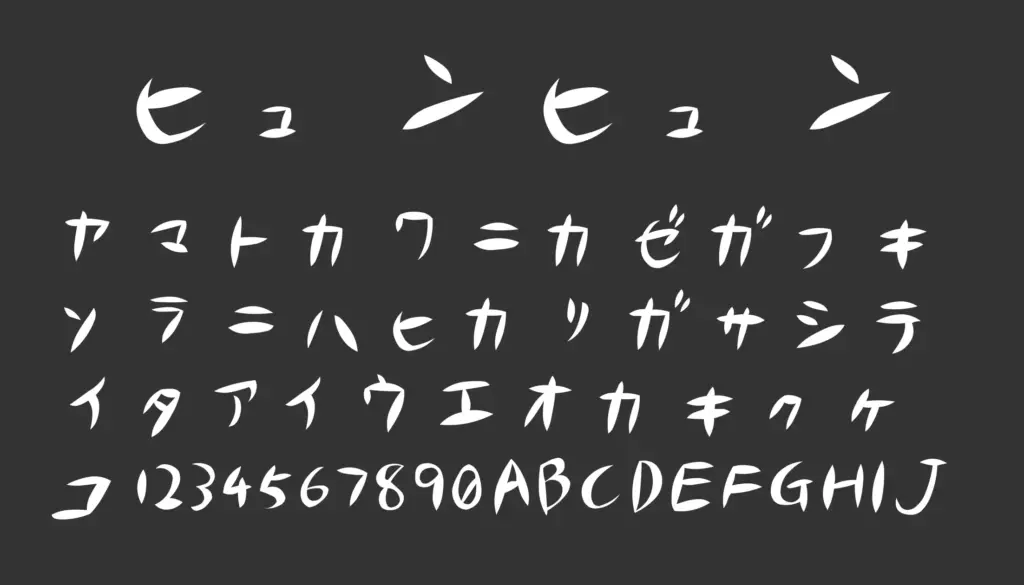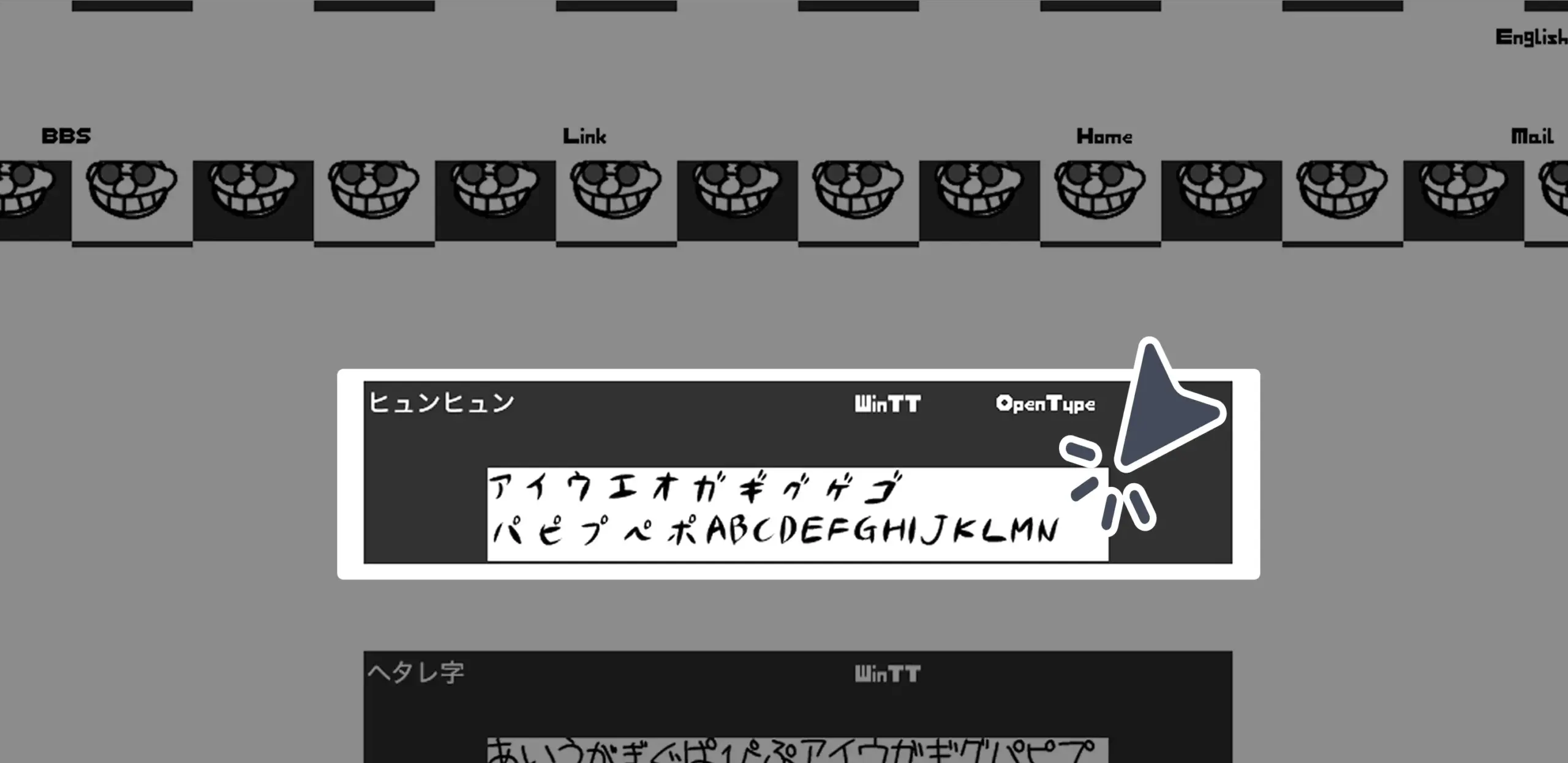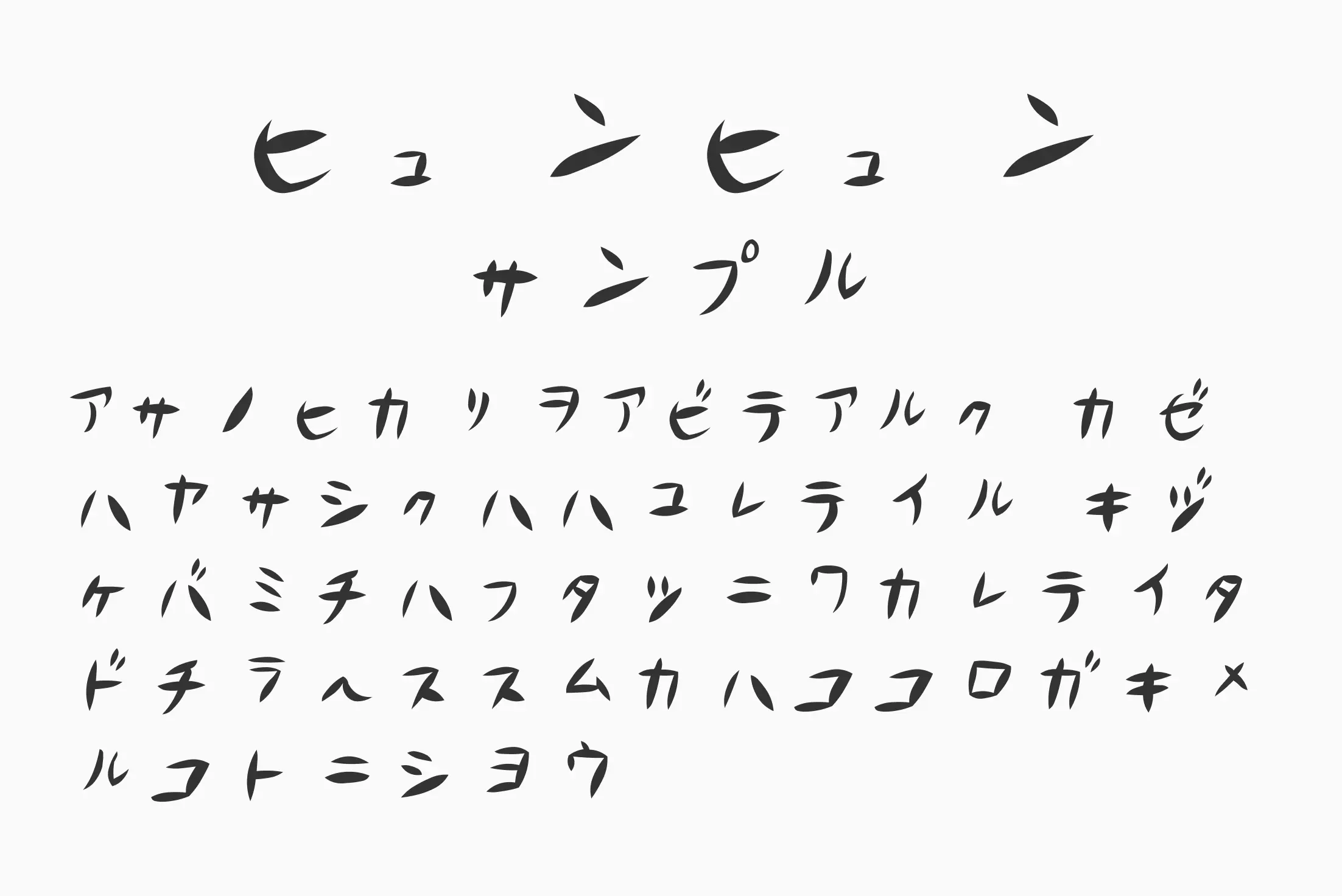
勢いよく走り書きされたような動きのある手書き風フォントです。スピード感のあるタッチが特徴で、ラフながらも印象に残るスタイルは、ポップなデザインや動画タイトル、軽快なロゴにぴったり。カタカナとアルファベットが中心で、元気さや遊び心を演出したい場面におすすめの書体です。
ヒュンヒュン
勢いよく走り書きされたような動きのある手書き風フォントです。スピード感のあるタッチが特徴で、ラフながらも印象に残るスタイルは、ポップなデザインや動画タイトル、軽快なロゴにぴったり。カタカナとアルファベットが中心で、元気さや遊び心を演出したい場面におすすめの書体です。